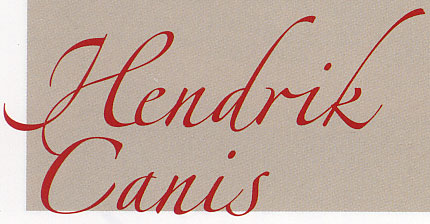
ライノタイプフォントが世界中でどのように使われているのか?
フォントの使用例です。
是非、画面をクリックして大きな画像をご覧下さい!
ウェブサイト: "casema" |
小冊子: "Kulturzentrum Stiftshof Backnang" |
パンフレット: "Unsehbar" |
パンフレット: "Partner Berlin |
ITC Johann Sparkling™
Viktor Solt, 1998
ITC Johann Sparkling は、オーストラリア人デザイナー Viktor Sole 氏が作業しました。「ITC Johann Sparkling は、走り書きのようないわゆる本物の筆跡と非常にフォーマルなコッパープレートスクリプト間のギャップを縮めることを目的にしている」とSolt 氏は言っています。また「私は非常にフォーマルなカリグラフィには興味がなく、迅速で人的な感じがするスクリプトに興味を持っています。いつも私はいくつかの歴史的なサンプルから始め、それらのソースをただ単にコピーするのではなく、自分独自の筆跡の中にそれらを組み込んでいきます。最大で約2週間位かかり、個々のスクリプトが自分のものに仕上がるまでにはたくさんの紙を使います。勿論、個々のレタリングする仕事としては決して経済的なやり方ではありませんが、それをデジタル化をすることによって今後使用する時にはずっとカスタムスクリプトを保存することができます。」ITC Johann Sparkling は、比較的大きめのポイント数で使用するといいでしょう。
↓↓迅速なスクリプト見本をご覧下さい。↓↓
| ITC Silvermoon™ Akira Kobayashi, 1998 |
Neue Hammer Unziale™ |
| 懐かしい雰囲気、ノスタルジックでロマンチックな ITC Silvermoon は、ヘッドラインや短いテキストでポイント数12以上に設定して使用することをお勧めします。 | Neue Hammer Unziale は、証明書、卒業証書、免許状に使用するのにも最適で ITC Silvermoon と同じくヘッドラインや短いテキストでポイント数12以上に設定して使用することをお勧めします。 | ||||||||||